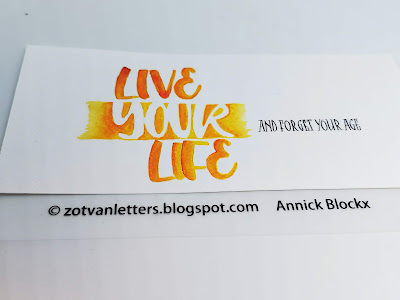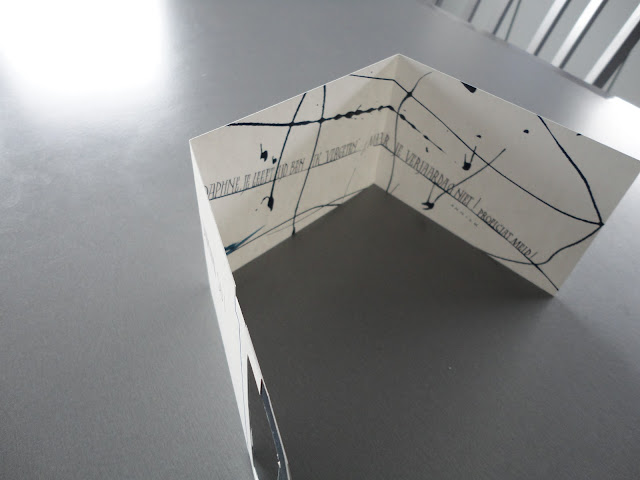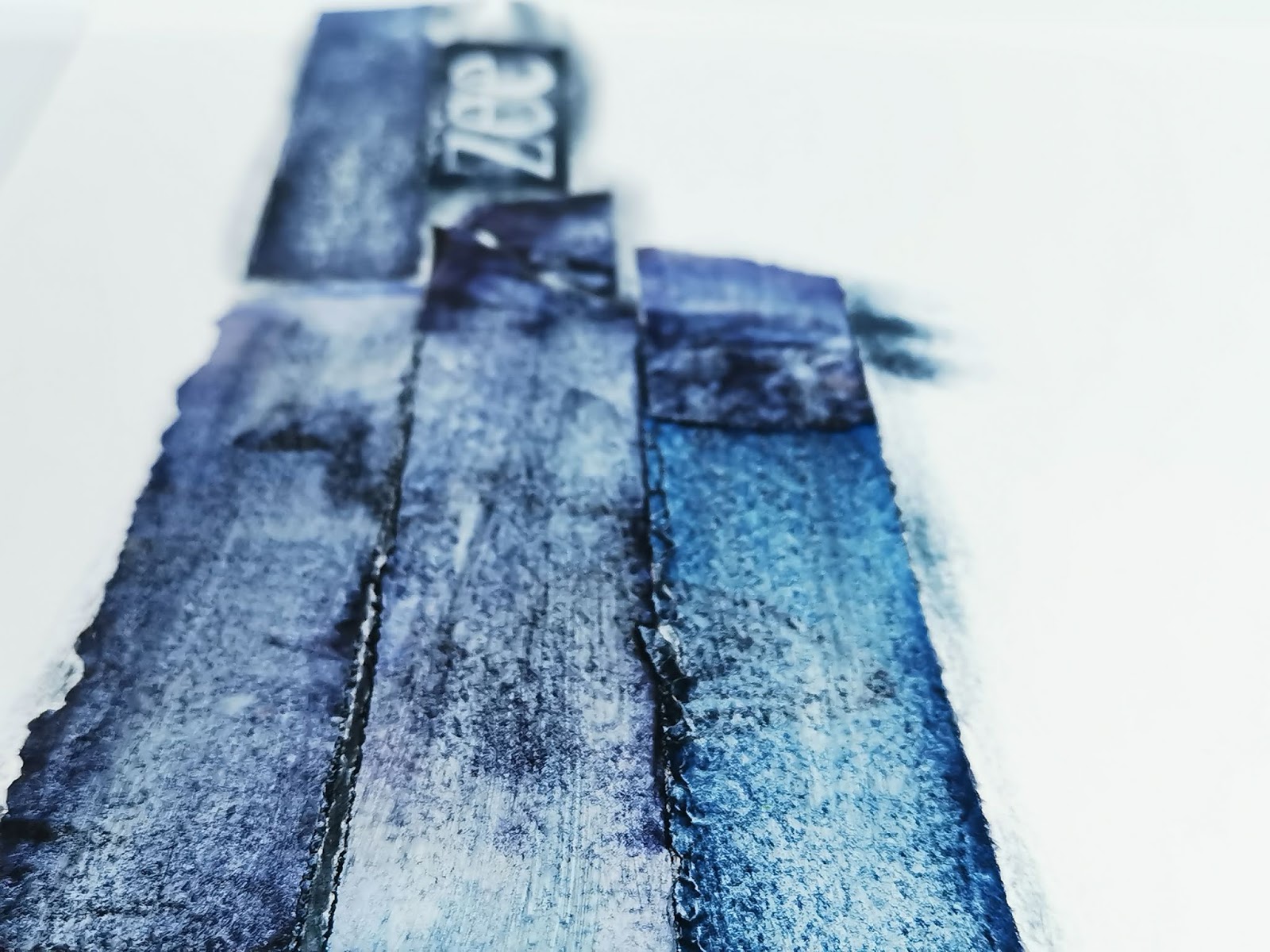
Af en toe moet er ook wat tijd zijn om te 'spelen', vind ik. Vandaar dat ik mijn aquarelletjes nog eens bovenhaalde om deze lettertjes in te kleuren.
De letters zijn niet door mij ontworpen. Ze komen uit een stansalfabet van een vriendin.
Now and then we need some time to 'play'. Hence I took out my watercolour paints to colour these letters.
I didn't design these letters myself, though. They're from a die-alphabet of a friend.
extra kalli-corona-project spring
het thema voor deze opdracht was: de lente
theme: spring
pencil exercise
potloodoefeningetje lente: alle tulpen gaan uit de bol.
theme: spring
pencil exercise
potloodoefeningetje lente: alle tulpen gaan uit de bol.
extra post: kalli-corona-project 1
Dit las ik op de FB pagina van het zomerproject (Ann Arnauts) waaraan ik nu al een paar jaar meedoe
"Geen cursussen of workshops om naartoe te gaan, geen vertier in café's, restaurants, cinema of theater. Gelukkig hebben we onze hobby nog. Daarom lanceer ik het kalli-corona-project. Zelfde systeem al een zomerproject : Iedereen kan lid worden. Iedereen mag opdrachten in de groep zetten. Bedoeling is dat je opdrachten uit het aanbod pikt en er iets moois van maakt. Het moois dat je maakt publiceer je in de groep. Op die manier blijven we onze hobby uitoefenen en blijven we in contact. Veel plezier ! Blijf gezond !"
The day before yesterday, Ann Arnauts , organiser of the summer projects, set up a new project: the kalli-corona-project. Everyone can post an assignment for the others , you pick the ones you want to do, experiment with it and post a picture of the result for others to see. In this way we can continue practicing our hobby, learn from each other AND stay in touch.
De eerste opdracht luidde: combineer het lettertype van Epps Evans met een fijne lijn op de achtergrond.
The first assignment: combine the Epps Evans type with a fine letter/fine lines.
En aangezien ik nu (nog) meer chocolade eet, besloot ik om de letters niet te schrijven, maar te knippen uit de zilveren chocoladewikkels.
Since I eat a lot (more) chocolate now, I decided to use the silver chocolate wraps to cut the letters out.
| result of too much chocolate... |
| Epps Evans type- source: pinterest |
| VERSCHIL: de kleine dingen maken het verschil - the small things can make a difference... |
| moeilijk om een goeie foto te maken met dit papier-always hard to photograph silvery paper |
drippings
Een andere techniek die ik regelmatig gebruik, is die van drippings, 1. omdat het super makkelijk is en 2.omdat het zo'n veelzijdige toepassingen heeft.
Another technique I like to use, is the one of dripping. 1. it's very easy to do and 2. the possibilities are endless.
Ik maakte er o.a. een kaart mee voor A. Hij werd 60 en is de enige man in onze kalligrafie'club'. Vandaar...
I made a birthday card for A. He turned 60 and is the only man in our calligraphy group....
Another technique I like to use, is the one of dripping. 1. it's very easy to do and 2. the possibilities are endless.
Ik maakte er o.a. een kaart mee voor A. Hij werd 60 en is de enige man in onze kalligrafie'club'. Vandaar...
I made a birthday card for A. He turned 60 and is the only man in our calligraphy group....
Beek +punk and graphics
Na het maken van de collages vorige week, heb ik de tijd gehad om ééntje verder af te werken, lees: te voorzien van tekst. Aangezien ik met blauwe kleuren werkte, koos ik ook een tekst in hetzelfde thema 'beek' van Toon Hermans.
I've found the time to finish (= add the text) one of the collage projects I did last week.
Since I worked with blueish colours, I decided on the poem 'beek' (=stream in English) by Toon Hermans.
En vorige week bezocht ik ook de tentoonstelling 'punk en grafiek' in het designmuseum in Brussel. Ik laat jullie even meegenieten:
And last week I visited the exhibition 'Punk and graphics' in the deign museum in Brussels. I thought it was great !
I've found the time to finish (= add the text) one of the collage projects I did last week.
Since I worked with blueish colours, I decided on the poem 'beek' (=stream in English) by Toon Hermans.
En vorige week bezocht ik ook de tentoonstelling 'punk en grafiek' in het designmuseum in Brussel. Ik laat jullie even meegenieten:
And last week I visited the exhibition 'Punk and graphics' in the deign museum in Brussels. I thought it was great !